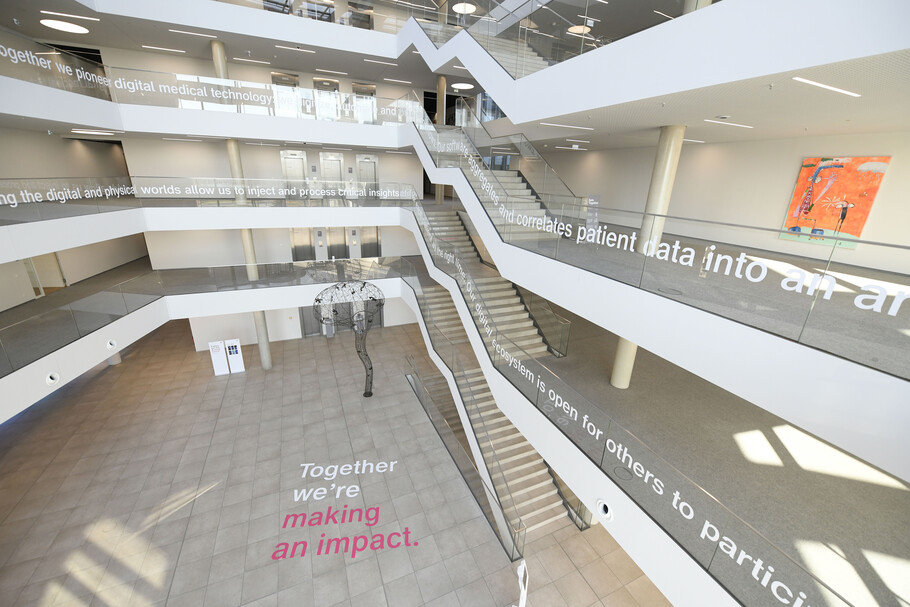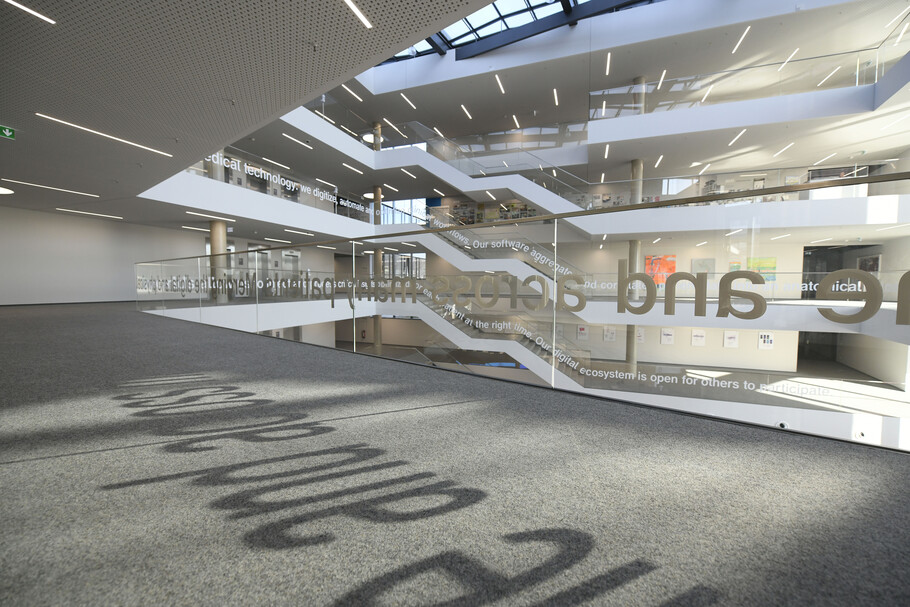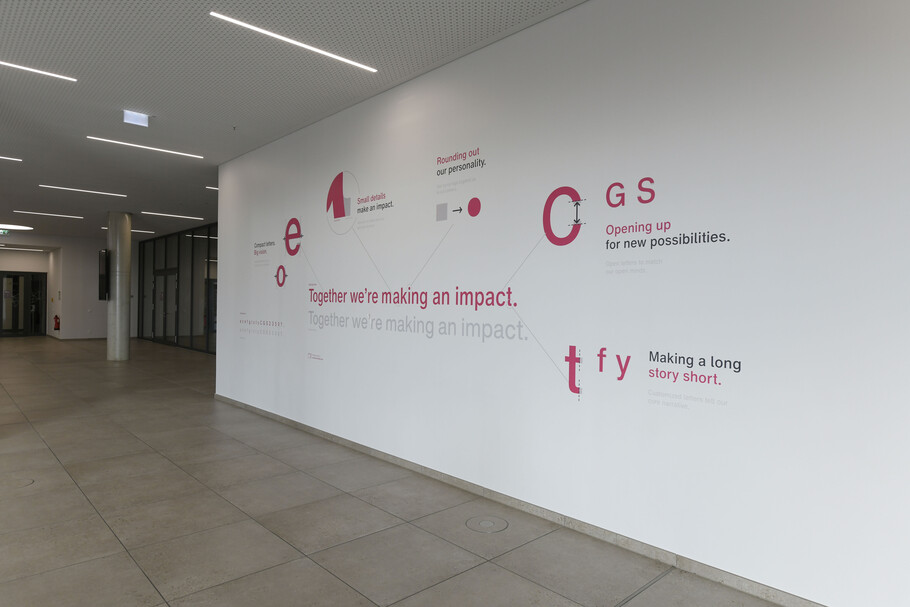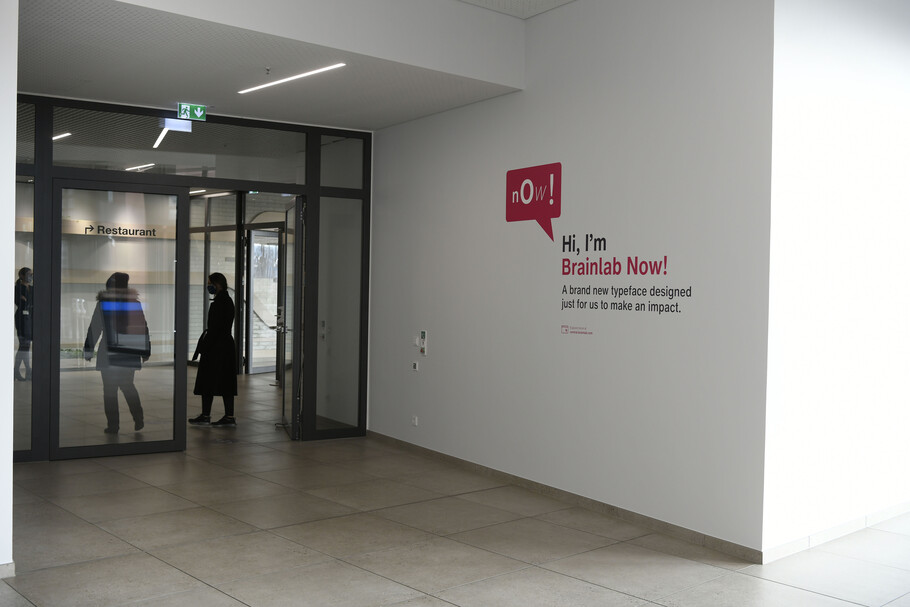
Une optimisation sur mesure d’Helvetica Now pour le rebranding de Brainlab.
“ Dès les premières conversations avec l’équipe de Brainlab, il était clair qu’ils avaient surtout besoin d’optimiser Helvetica plutôt que de la remanier. Cette approche était idéale pour Brainlab Now, car elle nous a donné la souplesse nécessaire pour tester de nombreuses itérations de proportion, de taille d’ouverture et d’espacement, ce qui nous a permis d’affiner le design en fonction de leurs besoins. ”
Tom Foley, Creative Type Director.
Leader mondial de la technologie médicale, Brainlab est une entreprise influente qui a transformé à grande échelle les soins de santé, notamment dans les domaines de l’oncologie, de la chirurgie et de la numérisation totale du bloc opératoire. Décidé pour un rebranding complet près de 30 ans après sa création, Brainlab s’est adressé à Monotype afin d’obtenir une version personnalisée d’Helvetica Now pour sa typographie de marque.
Comment une typographie réajustée peut-elle unifier le branding d’une entreprise de technologie médicale, ses qualités humaines et ses employés ?
Après 30 ans d’utilisation d’Helvetica, Brainlab était à la recherche d’une version modernisée de sa police de marque qui s’adapterait aux cas d’utilisation digital first et mettrait en valeur l’ADN unique de la marque ainsi que son approche centrée sur l’humain. Brainlab voulait une police d’entreprise distinguée, qui reflète sa personnalité, celle de ses produits et de ses employés.
“ Brainlab a toujours été axé sur les personnes... Nous savions qu’une police sur mesure participerait à synthétiser les aspects humains et numériques de notre entreprise et refléterait la façon dont nous fusionnons les mondes numérique et physique avec nos produits. ”
Stefan Vilsmeier, CEO/Founder.
Lorsque Monotype a annoncé la première refonte d’Helvetica en 35 ans, Brainlab a su que le Studio Monotype serait le partenaire idéal pour les aider à créer une expérience design adéquate. La version améliorée, baptisée Brainlab Now, offre des résultats sur mesure qui permettent à Brainlab de se différencier visuellement, avec l’avantage d’une intervention plus légère que la création intégrale d’une police personnalisée.
Dans le cadre de ce rafraîchissement majeur de l’identité de marque, la nouvelle police de caractères de Brainlab devait :
• S’imprégner de l’ADN de la marque
• Être digital first
• Avoir un impact dans toutes les langues
• Exprimer l’humanité aussi bien que la technologie
• S’inspirer du logo « serpent » de Brainlab
Les modifications.
En étroite collaboration avec l’équipe de Brainlab, le Studio Monotype a mis au point une police personnalisée moderne, humaine et conforme à l’esprit de la marque. Elle accorde aussi une attention particulière aux exigences pratiques telles que la lisibilité, l’évolutivité et la compatibilité linguistique.
« Dès les premières conversations avec l’équipe de Brainlab, il était clair qu’ils avaient surtout besoin d’optimiser Helvetica plutôt que de la remanier », explique Tom Foley, directeur de la création typographique. « Helvetica Now Text était notre point de départ, mais nous devions dessiner un nouvel ensemble de Condensed originaux, ainsi que plusieurs versions de caractères clés pour tester la lisibilité en petites tailles. Cette approche était idéale pour Brainlab Now, car elle nous a donné la souplesse nécessaire pour tester de nombreuses itérations de proportion, de taille d’ouverture et d’espacement, ce qui nous a permis d’affiner le design en fonction de leurs besoins. »
Pour créer une police flexible – pour tous, qui fonctionne partout, qui est unique et utile à tous niveaux –, nous avons condensé l’espacement de 92,5 % pour tenir compte du contenu assez verbeux et stimuler l’impact au travers des contraintes numériques. Nous avons également ajusté les proportions entre hauteur et graisse en fonction de la forme plus étroite de Brainlab Now et ajouté un style italique.
Brainlab GIF
En s’inspirant du logo emblématique de Brainlab créé en 1989, Brainlab et Monotype ont étudié comment les formes inhérentes au logo pouvaient être intégrées à la typographie. Nous avons ouvert une sélection de lettres minuscules et majuscules, de chiffres et de signes de ponctuation, et nous avons arrondi la ponctuation et les signes diacritiques, afin d’insuffler aux formes des lettres les attributs du logo.
Brainlab Snakey
Une marque, une typographie pour tous.
Brainlab Now fonctionne sur tous les points de contact, grands et petits, des installations d’exposition à grande échelle aux applications mobiles. Le Studio Monotype a veillé à ce que Brainlab Now soit accessible à tous les utilisateurs et a créé des caractères de différenciation qui maintiennent la cohérence à travers tous les points de contact possibles.
Brainlab Now évoque ce que ses marques représentent : une architecture et un écosystème ouverts. Elle offre une marque rafraîchie de manière réfléchie, « pour tous, partout ».
« Notre état d’esprit et notre personnalité sont clairement définis. Nous les appliquons à toutes les communications, nous sommes donc clairement entendus, rapidement reconnus et facilement mémorisés », déclare Tobias Schalkhausser, vice-président exécutif du marketing et du numérique. « Notre typographie répond à l’objectif de Brainlab. Elle instaure la confiance dans tout ce que nous faisons et avons fait, que ce soit passé, présent et futur. »